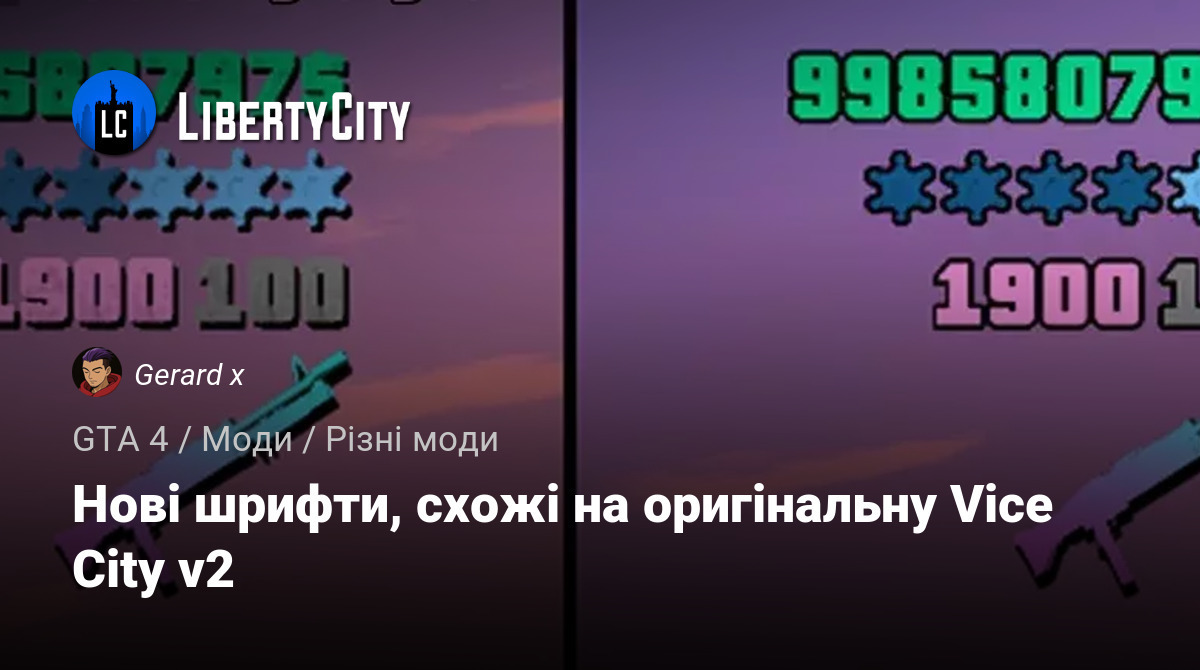
Нові шрифти, більш вірні оригіналу Vice City v2
Друга версія покращеного шрифту, який точніше передає стиль оригінальної GTA Vice City.
- Два стилі відображення грошей і набоїв
- :Класичний стиль — як у попередній версії мода;
- Definitive Edition Style — у стилі оновленої Vice City.
- Шрифт субтитрів з класичної версії гри;
- Виправлено відступи між літерами, покращено читабельність;
- Правильне відображення назв транспорту та локацій.